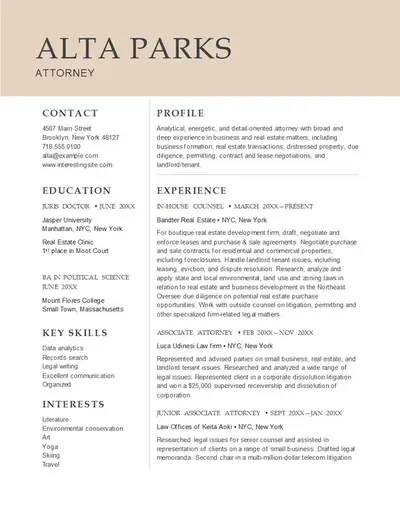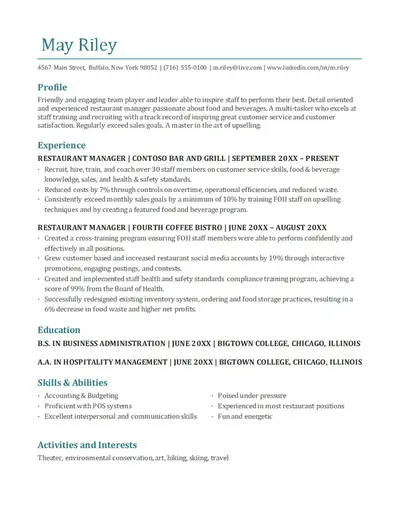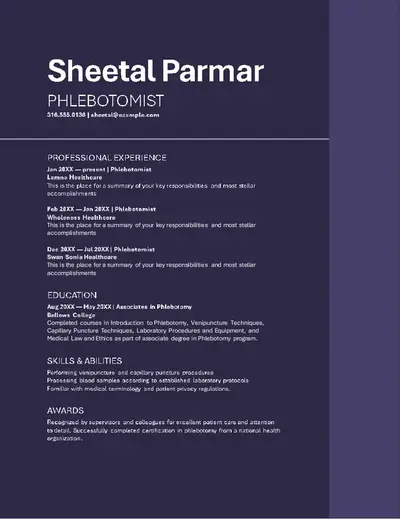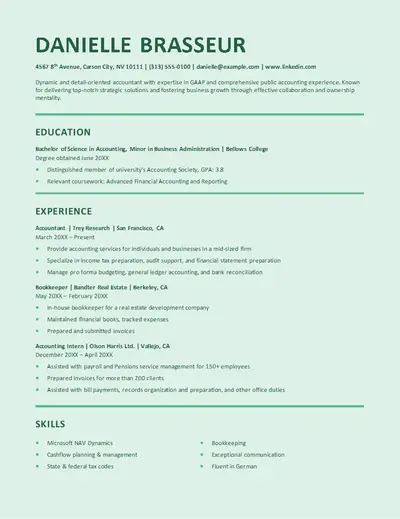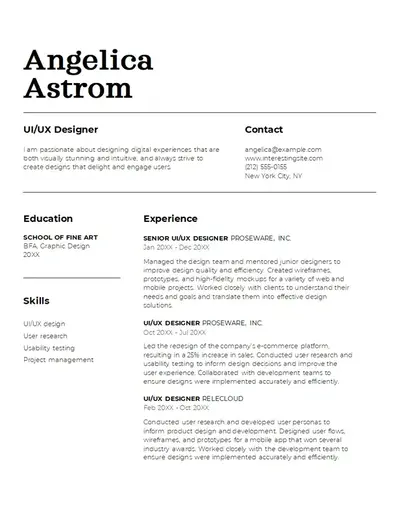
Вибір правильного шрифту резюме – один із найефективніших способів справити сильне перше враження. Шрифти можуть передати надійність і індивідуальність, підтримати професіоналізм і надати резюме професійного вигляду, щоб відобразити увагу до деталей.
Почніть роботу над добре складеним резюме з практичними порадами з вибору відповідних стилів і розмірів шрифтів. Дізнайтеся, як побудувати чітку ієрархію шрифтів, узгоджене форматування та створити вишукане резюме в Microsoft WordWord.
Шість найкращих шрифтів резюме для будь-якої вакансії
Найкращий шрифт для резюме не просто гарно виглядатиме на сторінці. Вибір шрифту визначає спосіб читання, ранжирування та запам'ятовування резюме. Нижче наведено найкращі професійні шрифти, за допомогою яких можна скласти резюме. Усі вони доступні в Microsoft WordWord.
1. Шрифт Calibri
Сучасний шрифт без зарубок, Calibri став золотим стандартом корпорації. Простий для читання, Calibri випромінює професіоналізм і авторитет. Завдяки яскравим і легким стилям цей шрифт без зарубок легко адаптується до будь-якого враження. Чудово підходить для таких професій, як юриспруденція, фінанси та охорона здоров'я, Calibri підходить для будь-якої ролі, де чистий, професійний вигляд є пріоритетом.
2. Шрифт Garamond
Класичний шрифт із засічками, Garamond є надійним вибором у професійних публікаціях та офіційних документах. Шрифт легко читається при менших розмірах, що надає резюме авторитетний і вишуканий вигляд. Garamond є сильним вибором для посад в академічних, видавничих, юридичних та виконавчих посадах, де цінується традиційна презентація з високим рівнем довіри.
3. Шрифт Montserrat
Монтсеррат надає резюме чистого, доступного вигляду. Це стандартне накреслення для друкованої реклами та міських вуличних вивісок, Montserrat ідеально підходить для резюме у творчій сфері, сфері здоров'я та нерухомості. Цей шрифт без зарубок виглядає жирним шрифтом і водночас надзвичайно чітким і легко сприймається.
4. Шрифт candara
Кандара — це витончений стильний варіант, який виглядає вишукано, але не надто офіційний. Цей шрифт легко читається та має вишуканий стиль. Він підходить для резюме з меншою кількістю тексту, як Комбінований формат резюме особливо добре підходить для стажування, програмного забезпечення та ІТ-посад.
5. Шрифт Cambria
Cambria — це традиційний, збалансований шрифт із засічками, який передає надійність і професіоналізм. Призначено для легке читання на екрані в тексті невеликого розміру, Cambria - це вишуканий варіант, який підійде для будь-якого резюме. Цей шрифт із засічками добре підходить для керівних посад, кадрів і керівних посад, і є чудовим варіантом для резюме інженерії та архітектури, оскільки дизайн підтримує математичні та наукові символи.
6. Шрифт Aptos
Aptos – це шрифт за замовчуванням у Microsoft WordWord і Microsoft 365, який поєднує сучасний стиль із надійною читабельністю й дає змогу створювати чітке резюме, яке можна сканувати. Призначений для читання на сучасних екранах з більш теплим, нейтральним тоном, Aptos — це гнучкий шрифт без зарубок, який адаптується до заголовків і основного тексту. Цей сучасний шрифт добре підходить для технологій, охорони здоров'я та управлінських програм.
7. Шрифт Arial
Arial – це чистий, простий шрифт без зарубок, який надає резюме професійного вигляду, який легко сканується. Його гнучкість робить його практичним вибором для резюме на різні посади та етапи кар'єри, незалежно від того, чи публікуються вони в цифровому форматі або друкуються. Цей акуратний, узгоджений шрифт особливо сумісний із корпоративними програмами, орієнтованими на клієнтів і бізнесом.
Вибір професійного шрифту для резюме
Вибравши короткий список відповідних шрифтів, наступним кроком буде пошук правильного варіанта Заява про прийом на роботу. Вибір правильного шрифту залежно від посади та рівня стажу передбачає розуміння культурних та професійних нюансів кожного сектора праці, а також враження, яке він повинен справити на потенційних роботодавців. Нижче наведено кілька рекомендацій, які допоможуть підібрати найкращий шрифт.
Враховуйте посаду та рівень
Різні посадові ролі та рівень стажу можуть впливати на те, наскільки креативним чи офіційним має бути дизайн резюме та шрифт. Подумайте про рівень стажу роботи, початковий, середній або старший, оскільки від цього залежить, скільки творчої свободи може зайняти вибір шрифту.
Наприклад: Calibri може надати резюме чистого, професійного вигляду для керівної ролі, тоді як Montserrat може додати більш сучасне відчуття до ролей у творчих сферах.
Розглянемо сферу роботи
Кожна професія та сфера роботи мають свій власний набір цінностей та очікувань. Резюме, створені для офіційних сфер діяльності, таких як юриспруденція, медицина, державне управління та фінанси, мають передавати надійність і професіоналізм, тому такі шрифти, як Aptos і Calibri, природно підходять.
Наприклад: резюме на посаду в юридичній фірмі підходить для традиційного шрифту із засічками, як-от Garamond або Cambria, тоді як посада в креативному агентстві може вимагати чогось більш спокійного, наприклад, Montserrat.
- Як змінити шрифт і розмір шрифту резюме в Word?
Відкрийте резюме в Word, виділіть текст, який потрібно оновити, і виберіть новий шрифт із розкривного списку шрифтів на вкладці "Основне". Налаштуйте розмір тексту, використовуючи поле розміру шрифту поруч. Щоб оновити всі заголовки або основний текст одночасно, клацніть потрібний стиль у колекції стилів правою кнопкою миші й виберіть команду "Змінити". Зміни автоматично застосуються до всього документа. Додаткові способи редагування та форматування документів у Word див. редактор документів.